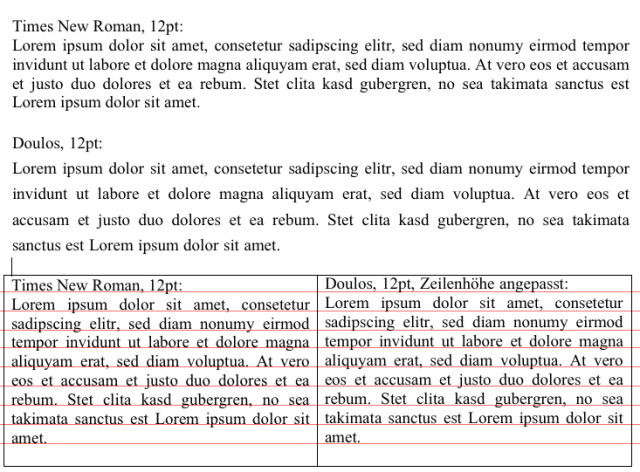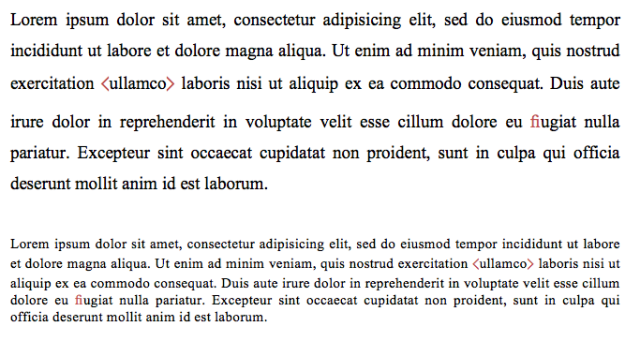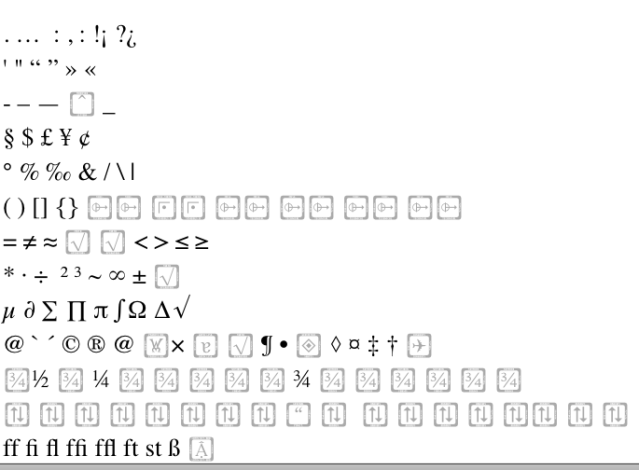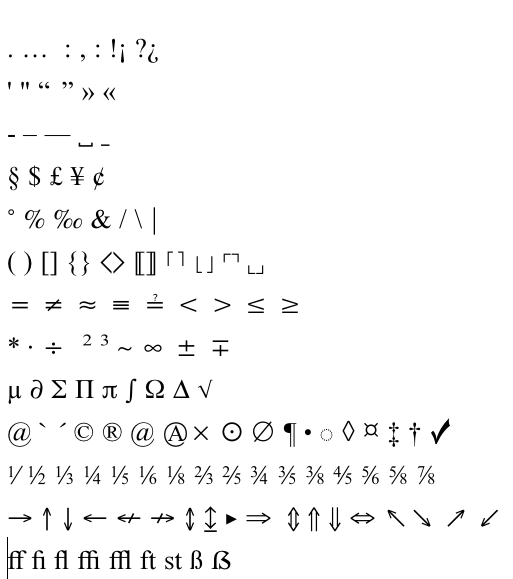
Zeilenhöhe Times New Roman vs. Doulos SIL
ich habe folgendes Problem: Wir schreiben an der Uni Hausarbeiten grundsätzlich in TNR mit 12pt und 1,5-fachem Zeilenanbstand. Soweit so gut wenn ich jetzt aber ein Zeichen aus dem Times-Klon Doulos (z.B. spitze Klammern) wird der Abstand in der Betreffenden Zeile vergrößert. (Siehe Beispiel)
Besonders auffällig ist das in kleineren Schriftgrößen und einfachem Zeilenabstand, z.B. in Fußnoten.
Kann ich das in Word verhindern?
Oder kann ich die Doulos so verändern, dass sie sich gleich verhält wie die Times?
Oder kann ich die fehlenden ZEichen in die TNR einbauen?
Ich könnte auch grundsätzlich mit der Doulos arbeiten, habe dann aber das Problem, dass der Zeilenabstand (und die Laufweite??) anders ist als bei der Times und ich rumfrikeln muss, bis es gleich aussieht…
Die einfachste Lösung wäre Wahrscheinlich, einfach die Doulos zu verwenden. Dann habe ich aber eine neue Frage: Kann ich in den Formatvolagen von Word die Times mit einem Klick durch die Doulos ersetzen?
PPS: Ich werde auf Dauer eh auf LaTeX umsteigen aber auch dort die Times (oder einen Klon) benutzen müssen. Aber viele Freunde können nur Word, daher wäre es für mich wichtig, auch dort eine Lösung zu finden.
ich kenne mich mit word nicht aus aber kannst du nicht den zeilenabstand festlegen in dem du sagst 14 oder 16 pt.?
die zeichen der anderen schrift haben andere größe/proportionen, daran liegt das mit dem automatischen zeilenabstand, da wird das »höchste« zeichen der zeile als basis genommen.
Du kannst in Word im Menü Format > Absatz den Zeilenabstand eingeben. Wenn du hier keine proportionale (1,5-fach) sondern eine absolute (Genau 18 pt) Formatierung eingibst, sollte das passen.
Die Times New Roman sollte doch auch über solche Klammern verfügen, oder? Oder betrifft es noch ganz andere Zeichen, die nur in der Doulos zu finden sind?
@TYPOGRAFSKI: Genau das ist das Problem. Kann ich denn die Proportionen der Doulos in der Font-Datei ändern?
@RobertMichael: Deine Klammern sind einfache Guillmets bzw. Größer-/Kleinerzeichen, das geht also nicht…
Ne, die Times* hat solche Klammern nicht. Und auch keine einzige Ligatur. Das sind die Zeichen, die mir besonders fehlen, was noch so fehlt kann ich nicht sagen…
Die Idee mit dem genauen Abstand werde ich aber mal versuchen! Danke für den Tip!
* Meine TNR ist die Systemschrift, die bei OSX 10.6 dabei war. Gibt es noch eine andere erweiterte? Wenn ja kann ich die irgendwie eifach ersetzen?
@TYPOGRAFSKI: Genau das ist das Problem. Kann ich denn die Proportionen der Doulos in der Font-Datei ändern?
rein theoretisch ja aber der aufwand ist zu groß, würde ich sagen oder kennst du dich mit fonteditoren aus und hast sogar welche?
Meine TNR hat auf jeden Fall Ligaturen und solche Klammern.
(Windows XP, umfangreiche OpenType-Times New Roman, Version 3.06, 2006)
Wenn die vertikale Metrik der Doulos nicht mit der der TNR exakt übereinstimmt, kommt es höchstwahrscheinlich zu Abweichungen.
Vertikale Metrik ist ein ziemlich kompliziertes Thema, da es aus technischer Sicht mehrere Maßsysteme gibt, und je nach Programm und Betriebssystem werden verschiedene Werte interpretiert oder ignoriert. Das sind technische Relikte, die aus Kompatibilitätsgründen noch mitgeschleppt werden, und weder Fonthersteller noch Programmhersteller trauen sich, etwas zu verändern ...
Möglichkeiten:
- Font mit einem Fonteditor bearbeiten (mühsam, komplexe Materie, etwas fehleranfällig, lizenztechnisch ok?)
- exakte Zeilenhöhe einstellen statt "vielfaches", wobei auch da nicht garantiert ist dass es dann ident ist.
- alles in der Doulos setzen und auf 0,9 Zeilenabstand setzen.
Gehe zu Menü:
Format/Formatvorlage:
Standard anklicken, dann Schaltfläche »«Ändern« …
Bei Formatierung die gewünschte Schrift auswählen, »Ok« und dann »Übernehmen«.
Dann wird in allen Formatvorlagen, die auf »Standard« basieren, die neue Schrift verwendet.
Möglicherweise musst du noch in exotischen Formatvorlagen die TNR ebenfalls ersetzen …
Also in meiner TNR sind die Klammern definitiv nicht und nicht alle Ligaturen. Hier mal ein Vergleich:
Times:
Doulos:
Ist schon ein Unterschied im Zeichenvorrat…
Ich hatte befürchtet, das sich die Doulos nicht so einfach als Times nutzen lässt. Schade. :cry:
Immerhin läuft sie scheinbar ähnlich anders als die TNR:
In den oberen Absätzen sind die Unterschiede groß (mehr Weißraum?) aber es passen gleich viele Worte in eine Zeile… komisch. In der Tabelle scheint der Unterschied dann nicht mehr so stark zu sein...
Die TNR eifach durch die Doulos zu ersetzten hab ich grad kurz versucht, das fällt aber auf, weil die TNR ein g mit Kringel (hat das nen »richtigen« Namen?) hat und die Doulos zwei Versionen einmal mit Kringel einmal normal und Word sich in dem Fall für das ohne Kringel entscheidet. Das gefällt mir nicht, ich weiß aber auch nicht, wie ich das ändern kann…
Pages dagegen verwendet das Kringel-g und auch in der Schriftsammlung wird in der Ansicht »Beispiel« wird sowohl bei der Doulos als auch bei der TNR das Kringel-g gezeigt.